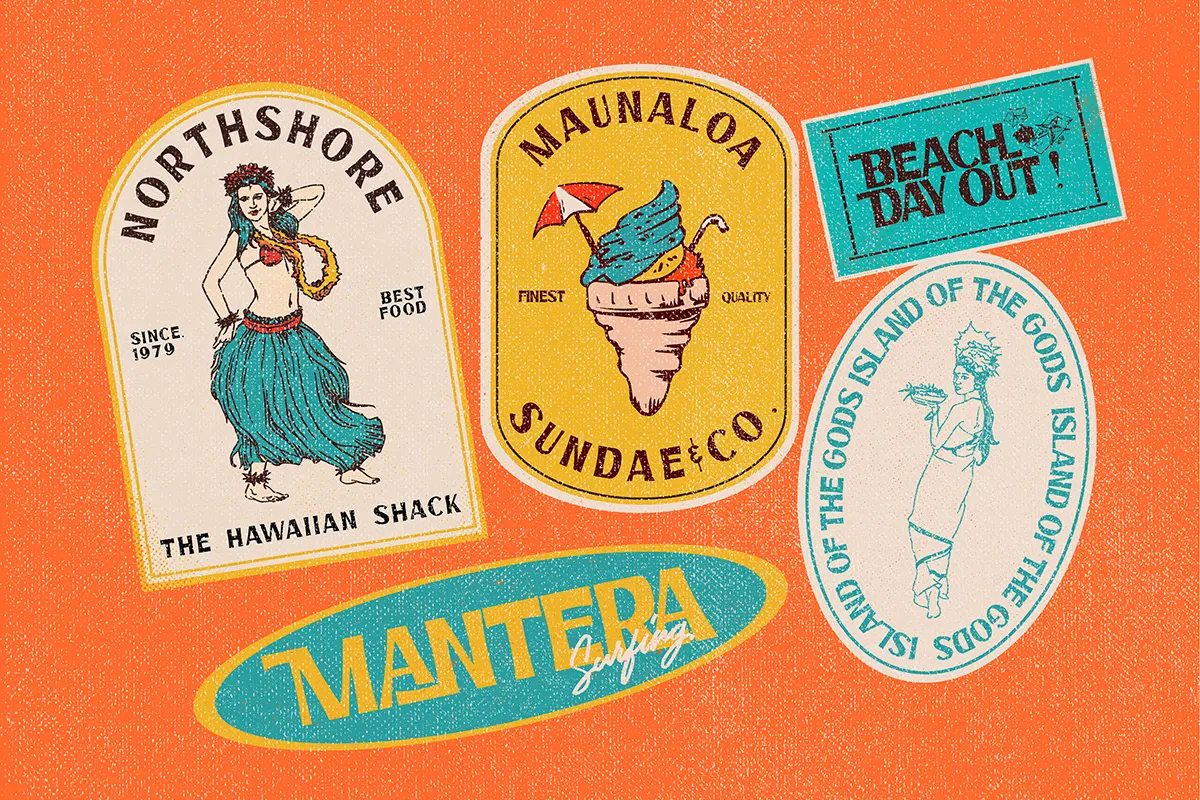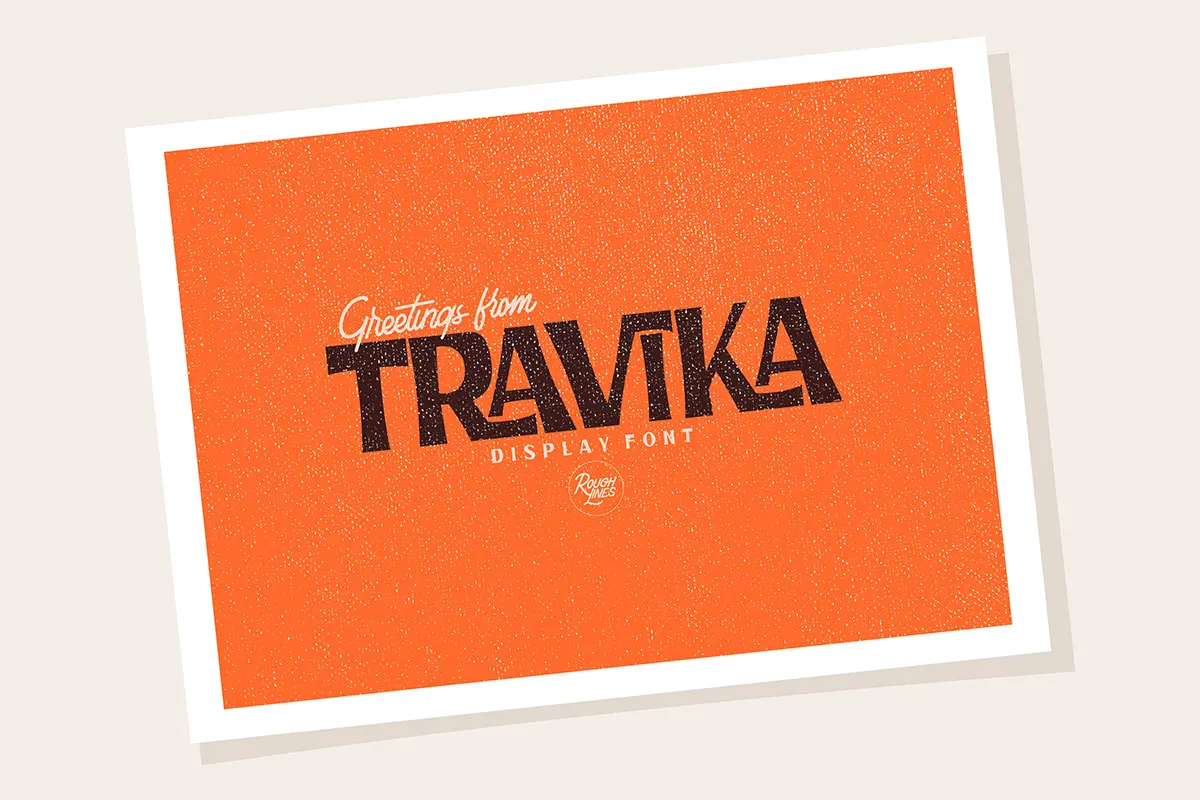
فونت کلاسیک و رترو
فونت Travika یک فونت نمایشی بولد و ضخیم است که با سبک قدرتمند و چشمگیر خود، نوشتهها را برجسته و متمایز میکند. این فونت به دلیل انعطافپذیری بالا، برای طیف وسیعی از پروژههای طراحی مناسب بوده و میتواند به هر طرحی جلوهای خاص و حرفهای ببخشد. همچنین به دلیل PUA Encoded بودن، دسترسی به تمامی گلیفها و سوئشها بهسادگی امکانپذیر است.
⭐ ویژگیهای محصول
- طراحی بولد و ضخیم برای جلوهای قدرتمند
- مناسب برای پروژههای نمایشی و تبلیغاتی
- دسترسی کامل به گلیفها و سوئشها با PUA Encoding
- سبک چندمنظوره و انعطافپذیر برای انواع طراحیها
🎯 موارد استفاده
- طراحی لوگوهای مدرن و چشمگیر
- ساخت پوسترهای تبلیغاتی و هنری
- استفاده در سرتیترها و بنرهای دیجیتال
- افزودن به پورتفولیو طراحان گرافیک و تایپوگرافی